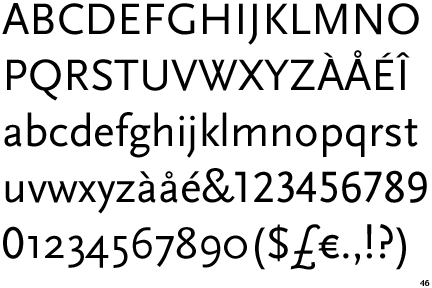
Welche Schrift ist das
Bei der Auflösung kann ich nur raten. Mein Tipp wäre die Syntax als Start für die Suche.
Geh mal zu http://www.identifont.com/ und lasse Dir alle der Syntax ähnlichen Schriften anzeigen. Da sollte noch die eine oder andere ähnliche Schrift zu finden sein.
leider,noch nicht die richtige dabei.
(auch bei identifont)
Markant sind vor allen dingen
die Buchstaben »G« und »R«
Die Frage ist nur, ob es sich wirklich um die Scala handelt. Mit scheint, dass es klitzekleine Unterschiede in den Rundungen einiger Buchstaben gibt. Wobei die Vorlage da nicht ganz so aussagekräftig ist … :-?
Vielleicht ist es ja die Seria oder Nexus.
1Spruch! Bei denen hat das G einen waagrechten Balken und das C ist senkrecht abgeschnitten. Die können es also definitiv nicht sein. Hier lege ich dem werten Forum das Beweismaterial vor:
FF Nexus: http://www.identifont.com/show?AKL
FF Seria Sans: http://www.identifont.com/show?3SW
Dann wurde die aber horizontal etwas gestreckt, oder?
Ja, das kommt hin :-)